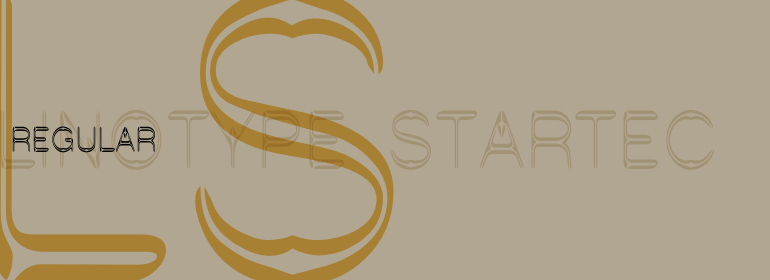
Linotype Startec™
Linotype Startec™,这款字体结构工整、笔画清晰,兼顾美观与易读性,适用于标题、正文、海报、包装、LOGO 等多种场景。字形优雅稳定,风格百搭耐看,适配日常排版与创意设计,让文字呈现更舒适、更具质感。Linotype Startec™一笔一画,皆是细节,以均衡的比例、流畅的线条打造舒适视觉体验,字形端正大气,风格简约现代。无论是商业设计、品牌宣传还是日常排版,都能轻松驾驭,让文字更有格调与力量。Linotype Startec™字体下载。
Linotype Startec, from Jan Tomás, is part of the TakeType Library, chosen from the entries of the Linotype-sponsored International Digital Type Design Contest 1999 for inclusion on the TakeType 3 CD. This is another fun font from Tomás, who also designed Alphabat, and the two share some characteristics. Linotype Startec is an outline font whose unique forms are reminiscent of futuristic dreams and space adventures. It should be used in point sizes of at least 18, but the phrase 'the bigger the better' fits this font well. The careful details and figures of the alphabet turn into UFOs and space ships from another world when set in very large point sizes. Linotype Startc is best for very short texts and headlines.